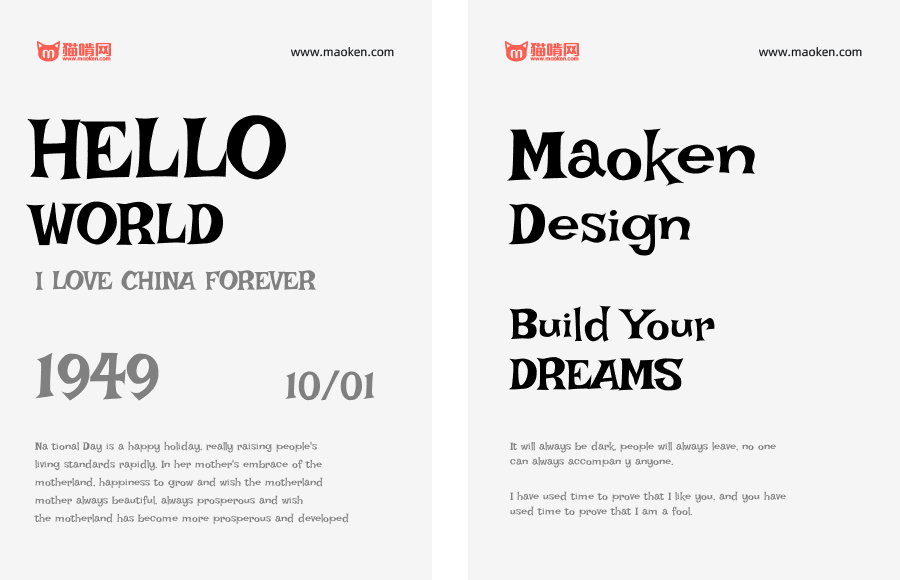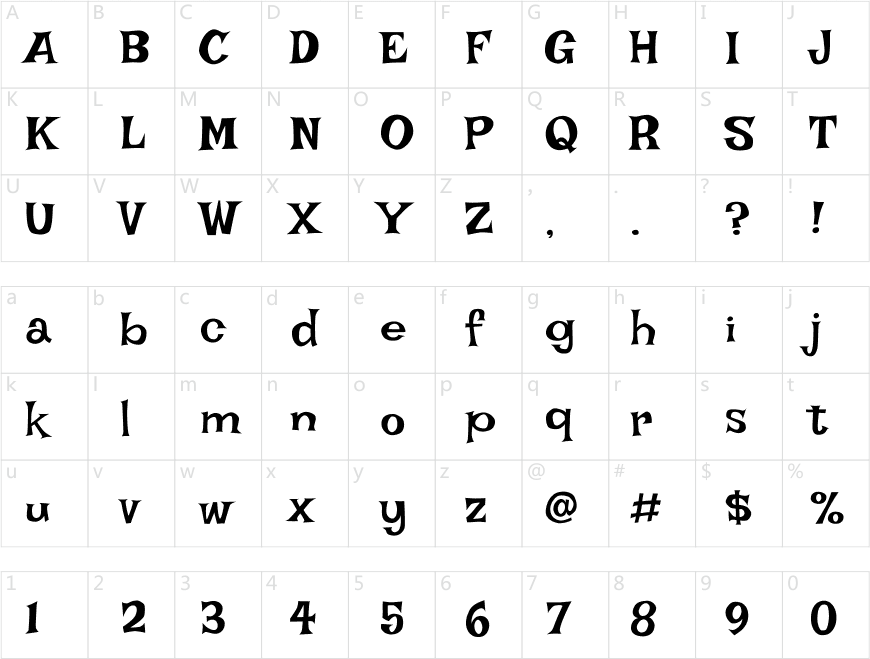
Irish Grover
来认识一下爱尔兰格罗弗字体!它可不是美国育犬协会(AKC,American Kennel Club)认证的新犬种,也不是什么美味的季节性皮尔森啤酒。这是一款由Squid推出的新展示字体,既有趣又张扬,比前面提到的那些可能性强太多了。重点是,它还是免费的!可别拿狗或者啤酒来跟它比。